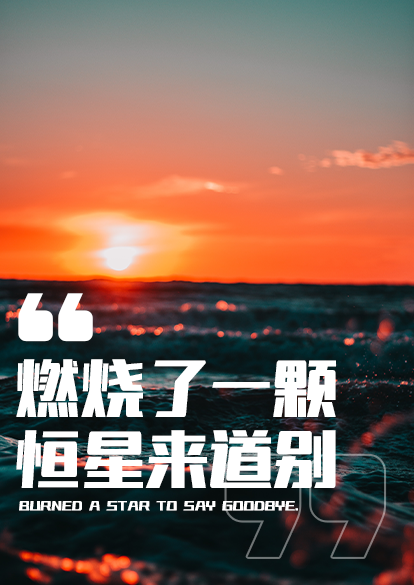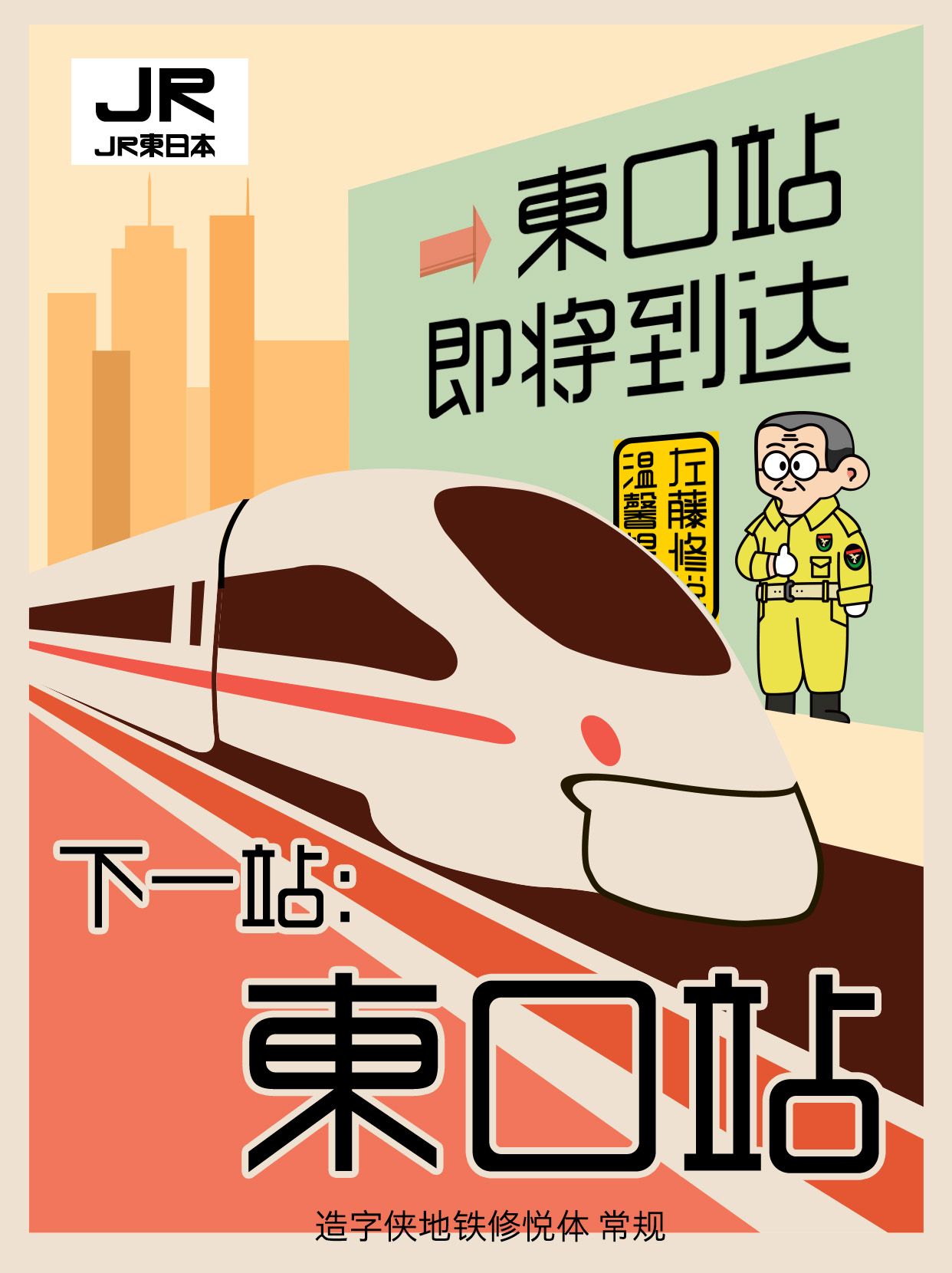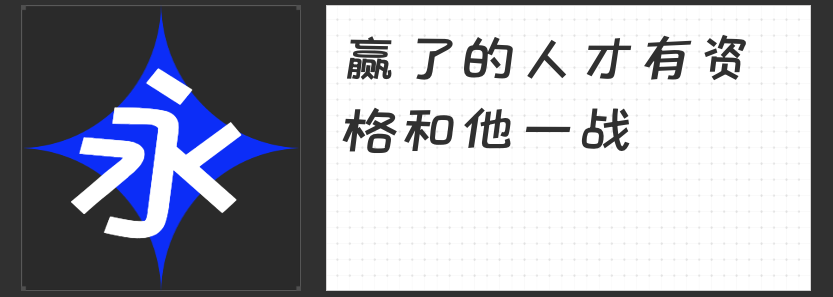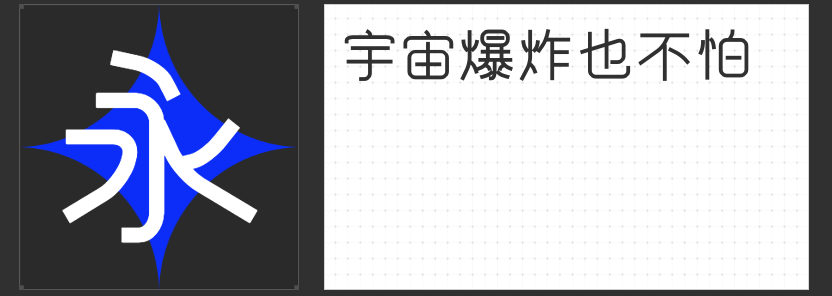
创意黑体字体推荐:独特风格,点亮设计灵感
在当今的设计领域,创意黑体字体凭借其独特的风格和强大的表现力,成为了许多设计师的首选。本文将为您推荐四款各具特色的创意黑体字体,它们不仅在视觉上引人注目,还能在不同的设计场景中展现出独特的魅力。
1. 励字多元宇宙简
“励字多元宇宙简”是一款圆体黑体字体,将传统的折笔处变为圆弧形状,使整个字体显得圆润且不失力度。笔画粗细均匀,字形紧聚,但不失美感,给人一种更加柔和、舒适的感觉。这款字体特别适合用于儿童读物、教育材料、品牌形象设计等需要传递温暖和亲切感的场景。其圆润的线条和均匀的笔画能够有效提升设计的亲和力和吸引力。
2. 造字侠地铁修悦体 常规
“造字侠地铁修悦体 常规”源于地下铁工作员佐藤修悦的真切热心,他为了方便地铁乘客快速寻路,用胶带在墙上拼贴成醒目的指路文字,增加了乘客的通行效率。这款字体的造型方正,笔画切口平直,充满了胶带制作带来的几何风格。结构上保留了人工拼贴的手工不规律性,造成了多变的重心和留白,风格与视觉的强烈冲击使字体排版时充满趣味与个性。这种独特的风格不仅能够吸引人们的注意力,还能够在各类海报、导视系统、公共标识等设计中发挥出色的效果,提升信息传达的效率和吸引力。
3. 励字磅礴简 高
“励字磅礴简 高”是一款极具实验性的黑体字体,采用了斜体与正体的融合设计。左侧倾斜的手法在整体稳重大气的字形中增添了几分灵动,右侧的垂直设计则支撑起整个架构,形成了“气势磅礴,万壑争流”的视觉效果。这种设计不仅令人联想到“不识庐山真面目,只缘身在此山中”的意境,还能够为设计带来一种独特的张力和动态感。这款字体特别适合用于高端品牌的广告宣传、大型活动海报、企业宣传片等需要展现强大气场和高端感的场合。
4. 字圈也字漫画粗黑体
“字圈也字漫画粗黑体”是一款醒目个性的粗体黑体字,顾名思义,这是一款专为漫画设计的字体。笔画整体向右倾斜,个性十足,给人一种充满活力和动感的感觉。这款字体不仅适用于漫画书、插画设计等创意项目,还可以用于社交媒体文案、广告宣传、海报设计等需要吸引年轻受众的场景。其粗犷有力的笔画和向右倾斜的设计能够有效提升设计的视觉冲击力和趣味性。
这四款创意黑体字体各具特色,不仅能够满足不同设计需求,还能为您的作品增添独特的风格和魅力。无论是追求柔和舒适的圆体黑体,还是需要充满几何风格和手工质感的地铁修悦体,或是展现强大气场的磅礴简高,亦或是个性十足的漫画粗黑体,都能为您的设计带来新的灵感与创意。希望这些推荐能够为您的设计提供更多的选择,帮助您创造出更加出色的作品。